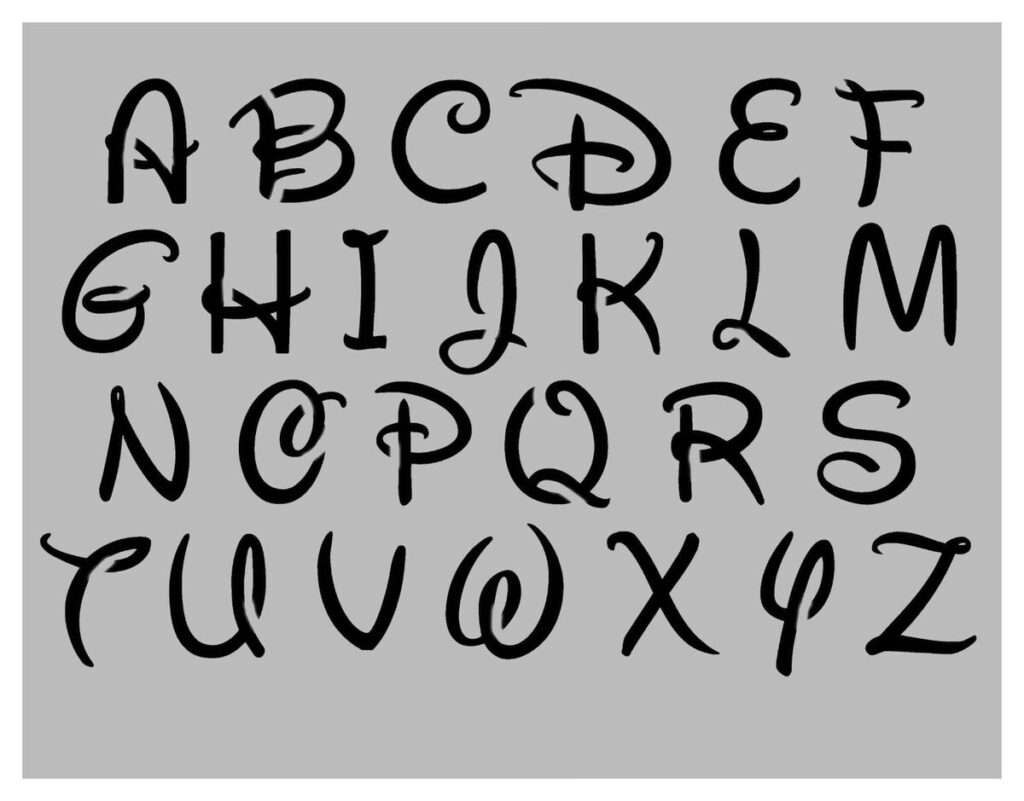
Disneys verden er mere end bare film, parker og karakterer; det er et univers fyldt med magi, nostalgi og en helt unik visuel identitet. En stor del af denne identitet ligger i de skrifttyper, der bruges – fra det øjeblikkeligt genkendelige logo til de specifikke titelskrifter for hver enkelt film. Disse skrifttyper bidrager i høj grad til at formidle stemningen, genren og sjælen i Disneys mange historier. Har du nogensinde undret dig over, hvilken skrifttype der gemmer sig bag den velkendte Disney-fortryllelse?
Når vi taler om 'Disney skrifttypen', tænker de fleste straks på det ikoniske logo. Denne skrifttype, der er synonym med brandet, kaldes officielt Waltograph. Den er direkte baseret på Walt Disneys egen, karakteristiske signatur – den håndskrift, der startede det hele. Waltograph er kendetegnet ved sine brede, livlige løkker og glatte, flydende kurver, der udstråler en følelse af både sjov og en vis tidløs elegance. Det er en skrifttype, der øjeblikkeligt vækker følelser af barndom, eventyr og ren magi hos folk verden over. Waltograph bruges ofte i forbindelse med brandet selv, på merchandise og i fan-kunst, hvor den fremkalder en stærk følelse af nostalgi og charme.
Men Disney-universet er enormt og mangfoldigt, og det samme gælder dets typografi. Ud over det klassiske logo bruger Disney en bred vifte af forskellige skrifttyper. Hver enkelt spillefilm, tegnefilm eller serie har ofte sin egen unikke titelskrifttype, der er designet specifikt til at afspejle netop den historie, de karakterer og den stemning, den repræsenterer. Tænk på de forskellige skrifttyper, der bruges til titler som To på flugt (Tangled), The Nightmare Before Christmas, Herkules eller Den Lille Havfrue. Hver især har de et design, der perfekt indfanger filmens essens. Dette betyder, at der ikke kun findes én 'Disney skrifttype', men snarere et helt bibliotek af skrifttyper, der hver især bidrager til magien.
For grafiske designere, fans og kreative sjæle, der ønsker at indfange et strejf af Disney-magi i deres egne projekter, er der heldigvis et væld af Disney-inspirerede skrifttyper tilgængelige. Disse skrifttyper, ofte omtalt som 'Disney dupe' eller lignende skrifttyper, er skabt med tydelig inspiration fra Disneys visuelle univers. Mange af disse er tilgængelige gratis til personlig brug, hvilket gør det muligt for alle at tilføje et strejf af fortryllelse til invitationer, plakater, fan-kunst eller andre kreative udfoldelser. Det er vigtigt altid at tjekke licensbetingelserne, da brug til kommercielle formål ofte kræver en betalt licens.
Lad os se nærmere på nogle af de mest populære og inspirerende Disney-lignende skrifttyper, der findes:
Mickey Ears Font
Denne skrifttype er en sjov hyldest til verdens mest berømte mus. Bogstaverne er enkle, fede og brede, men det mest karakteristiske er, at de er 'indkapslet' i en form, der ligner Mickey Mouses hoved med de karakteristiske ører. Selvom den måske ikke er den mest alsidige skrifttype, er den perfekt til Disney-temafester, børnefødselsdage eller andre begivenheder, hvor Mickey-magien skal være i centrum.
Mouse Memoir Font
Mouse Memoir skrifttypen tager inspiration fra den originale Mickey Mouse og 1950'ernes animation, herunder klassikere som Steamboat Willie, Anders And og Fedtmule. Den er karakteriseret ved et fedt, men finurligt design, der emmer af nostalgi og tegnefilmens guldalder. Denne skrifttype er ideel til lette og sjove projekter, såsom illustrationer, billedbøger eller invitationer til børnearrangementer, hvor man ønsker at fremkalde en klassisk tegneserie-følelse.
Malefic Font
Malefic skrifttypen er en hyldest til en af Disneys mest ikoniske skurke, Maleficent fra Tornerose. Skrifttypen er elegant, tynd, men alligevel skarp og kraftfuld – ligesom karakteren selv. Dens spidse kanter og kurver minder subtilt om Maleficents genkendelige hornede hovedbeklædning, hvilket tilføjer et unikt og dristigt element. Hvis du ønsker at tilføje et strejf af dristighed, elegance og en smule feminin styrke til dit design, er denne skrifttype et fremragende valg.
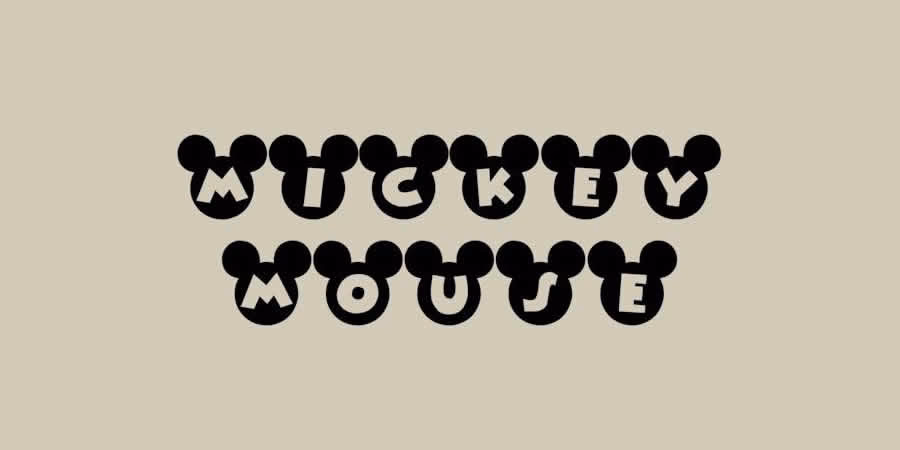
AL Cinderella Font
Hvem kan glemme den tidløse historie om Askepot? AL Cinderella skrifttypen er en hyldest til denne klassiske film og dens visuelle stil. Bogstaverne udstråler elegance og sofistikation med smukke, flydende linjer, der minder om Askepots kjole og tiara, da hun deltager i ballet. Denne skrifttype er perfekt til projekter, der kræver et strejf af eventyrlig elegance, såsom bryllupsinvitationer, ballerkort eller design relateret til prinsesse-temaer.
Monster AG Font
Inspireret af firma-identiteten i filmen Monsters, Inc., er Monster AG skrifttypen fed, stor og robust. Bogstaverne signalerer styrke og en vis industriel, men dog tegneserieagtig, følelse. Den er ideel til projekter, hvor man ønsker at formidle en følelse af noget stort, legende og lidt 'monstrøst' på en venlig måde, perfekt til temaer omkring monstre, energi eller legende virksomhedsidentiteter.
FL Firehouse Pup Font
Denne charmerende skrifttype tager inspiration fra en af de søde hvalpe i Disneys klassiker 101 Dalmatinere. Det geniale ved denne skrifttype er, at hvert bogstav er designet til at ligne, at det sidder inde i et hundehalsbånd. Det er et kreativt og uforglemmeligt design, der er perfekt til alt kæledyrsrelateret – invitationer til en hvalps fødselsdag, skilte til dyrlægeklinikker eller materialer til at øge bevidstheden om kæledyrssikkerhed. Den er legende, sød og meget genkendelig.
Princess and The Frog Font
Denne skrifttype, inspireret af filmen Prinsessen og Frøen, har et klassisk og tidløst udseende. Selvom den er relativt enkel, har den en stærk appel. Den bruger fede serif-karakterer, der er forstørret og designet med former og strøg, der minder om traditionelle skrifttyper, men med et strejf af New Orleans' charme og eventyrets magi. Den er god til projekter, der kræver et klassisk, men dog eventyrligt udtryk.
Nightmare Before Christmas Font
Tim Burtons The Nightmare Before Christmas er kendt for sin unikke, makabre og gotiske stil, og skrifttypen inspireret af filmen fanger denne stemning perfekt. Nightmare Before Christmas skrifttypen består af tynde, skæve linjer med krumninger og detaljerede kanter, der tilføjer et mørkt og gotisk udtryk. Den er ideel til Halloween-relaterede materialer, uhyggelige invitationer eller projekter, der omfavner den charmerende, makabre æstetik fra filmen.
Frankenweenie Font
I tråd med den gotiske og lidt uhyggelige stil fra The Nightmare Before Christmas, er Frankenweenie skrifttypen inspireret af Tim Burtons stop-motion film af samme navn. Denne skrifttype er tyk, fyldt med kurver, skævheder og rynker, designet til at tilføje et strejf af mystik og uhygge til ethvert design. Den er perfekt til Halloween, gyser-temaer eller projekter, der kræver en håndtegnet, lidt forstyrret, men dog elskelig, følelse.
Tangled Font
Skrifttypen inspireret af filmen To på flugt (Tangled) er – passende nok – inspireret af Rapunzels hår. Den er elegant og smuk, med tykke linjer, rige teksturer og sjove, stilfulde krøller på nogle af bogstaverne. Hvis du ønsker at tilføje en dimension af stilfuldhed, eventyr og en smule legende elegance til dit design, er Tangled skrifttypen et oplagt valg.
Comic Impact Regular (Donald Duck Font)
Denne skrifttype er en fed og legende type, der ofte bruges i tegneserier. Med sine tykke, afrundede bogstaver og overdrevne kurver har den en sjov og dynamisk følelse, perfekt til at formidle spænding og action. Den siges at være inspireret af typografien forbundet med Anders And. Comic Impact Regular kan bringe en følelse af nostalgi og humor til forskellige designs, fra børnebøger og plakater til digitale medier, og dens distinkte stil kan fange opmærksomhed og tilføje personlighed til ethvert projekt.
Disse er blot nogle få eksempler på de mange Disney-inspirerede skrifttyper, der findes. Designere og fans fortsætter med at skabe nye varianter inspireret af nye film og serier, hvilket sikrer, at der altid er nye måder at fange Disneys magi på i grafisk design.
Ofte Stillede Spørgsmål om Disney Skrifttyper
Her er svar på nogle hyppige spørgsmål om Disneys skrifttypebrug:
Hvad hedder den officielle Disney skrifttype?
Den skrifttype, der ofte associeres med det klassiske Disney-logo og er baseret på Walt Disneys signatur, er kendt som Waltograph. Det er den mest ikoniske skrifttype i Disneys brand-identitet.
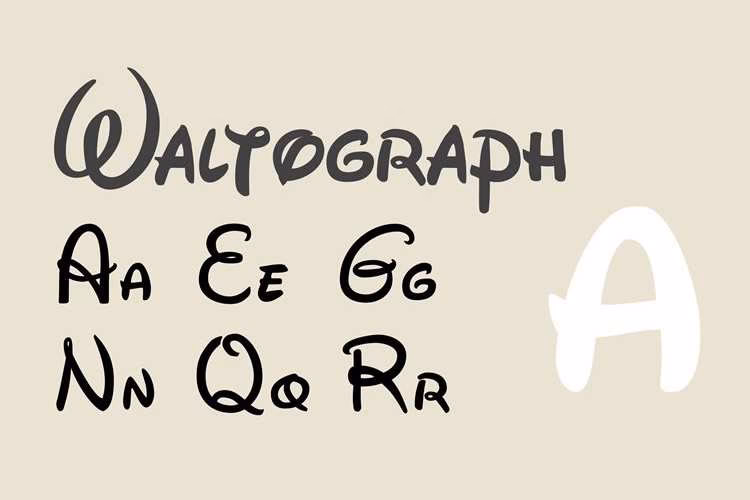
Er alle disse Disney-inspirerede skrifttyper gratis?
Mange af de skrifttyper, der er inspireret af Disney-film og -karakterer, er skabt af fans eller designere og er tilgængelige som gratis downloads til personlig, ikke-kommerciel brug. Det er dog vigtigt at tjekke licensbetingelserne for hver specifik skrifttype, da nogle kan kræve en betalt licens for kommerciel brug, eller være en del af en betalt abonnementstjeneste.
Hvor kan jeg bruge Disney-inspirerede skrifttyper?
Du kan bruge dem i forskellige personlige grafiske designprojekter, såsom invitationer til børnefødselsdage, personlige plakater, fan-kunst, scrapbøger, skoleprojekter eller andre kreative hobbyer, hvor du ønsker at tilføje et strejf af Disney-magi. Husk altid at respektere licensen for den enkelte skrifttype.
Bruger Disney kun én skrifttype til alt deres materiale?
Nej, bestemt ikke. Mens Waltograph er central for Disney-logoet, bruger Disney en bred vifte af forskellige skrifttyper til filmtitler, markedsføringsmaterialer, merchandise og deres streamingtjeneste. Hver film og brand har ofte sin egen unikke typografi for at afspejle dens specifikke tema og stemning.
Hvilken skrifttype bruger Disney+ streamingtjenesten?
Streaming-tjenesten Disney+ bruger primært skrifttypen Avenir til sin brugergrænseflade på tværs af platforme. På Apple-enheder (iOS) kan den også benytte San Francisco Pro Display, som er Apples standard systemfont. Disse skrifttyper er valgt for deres læsbarhed og funktionalitet på digitale skærme, hvilket adskiller sig fra de mere dekorative skrifttyper, der bruges til filmtitler og logoer.
Sammenfattende er Disneys verden rig på typografisk variation, fra det ikoniske Waltograph til de mange film-specifikke skrifttyper og de moderne valg til digitale platforme som Avenir. Denne mangfoldighed af skrifttyper er en integreret del af Disneys evne til at fortælle historier og skabe magiske oplevelser. Udforsk de mange tilgængelige Disney-inspirerede skrifttyper og se, hvordan du kan bringe et strejf af denne fortryllelse ind i dine egne kreative projekter.